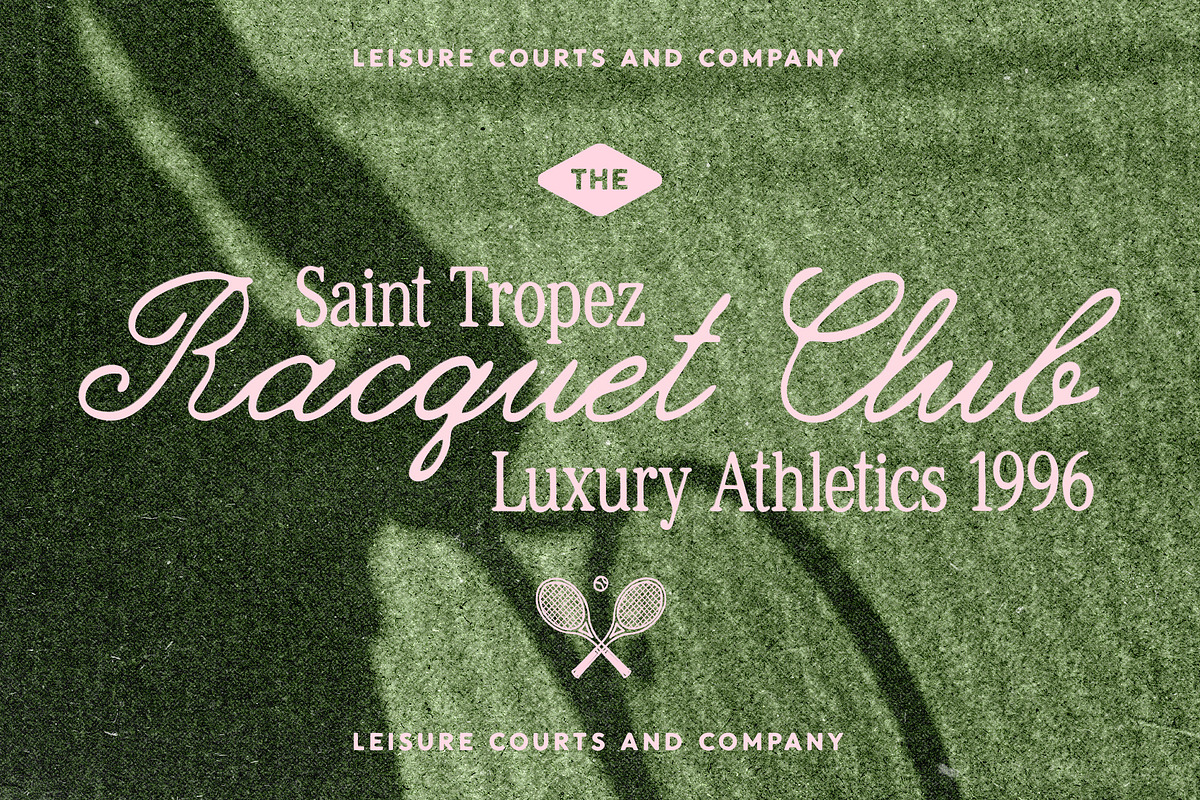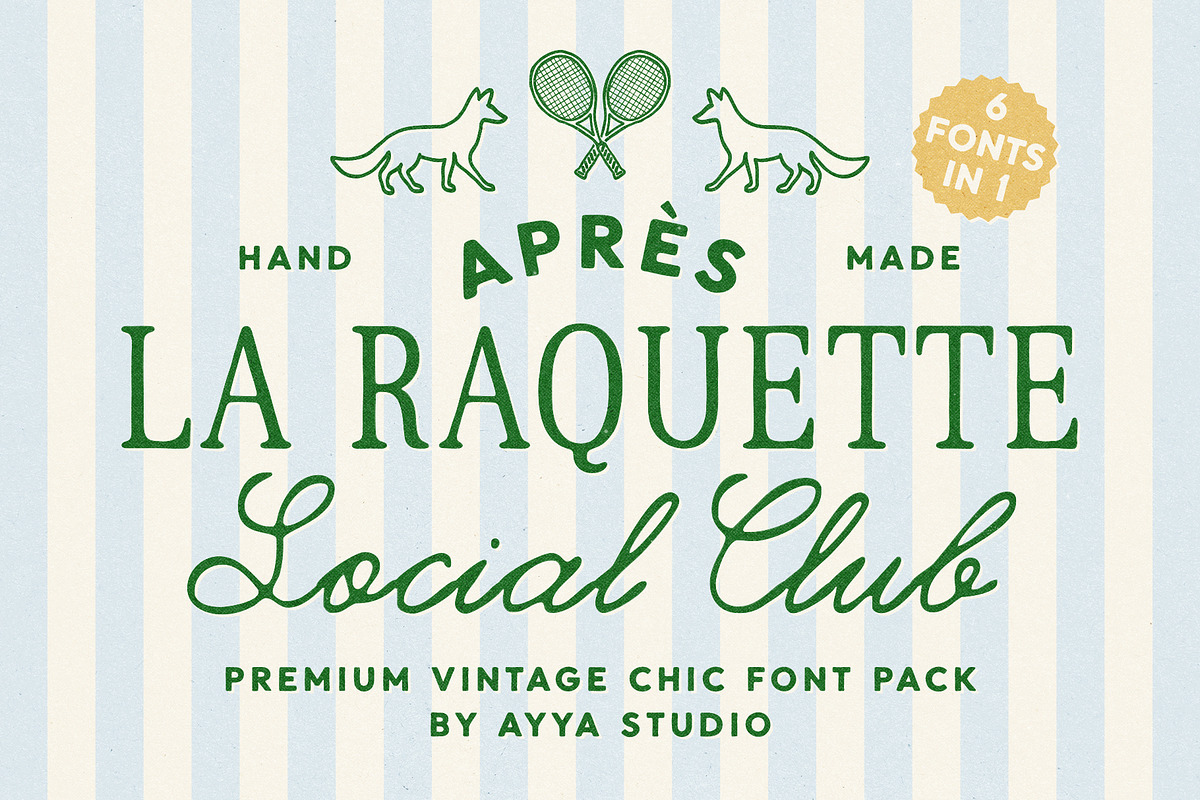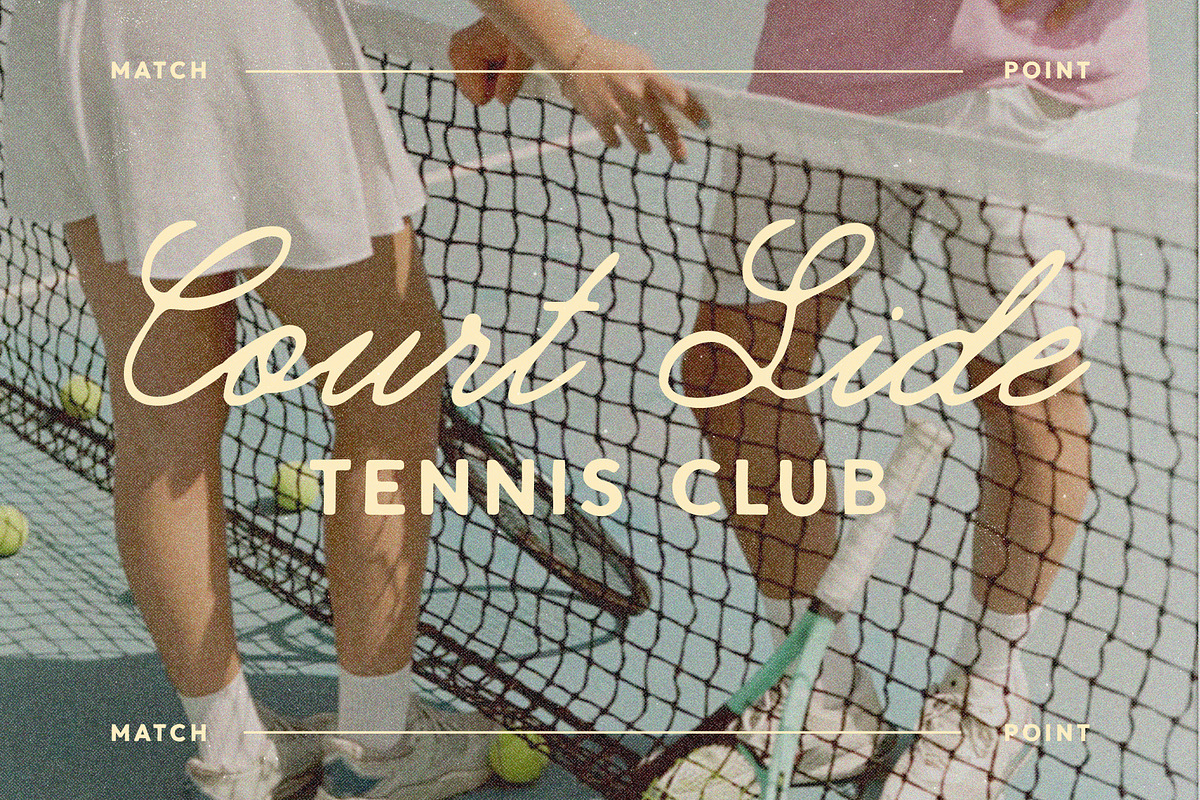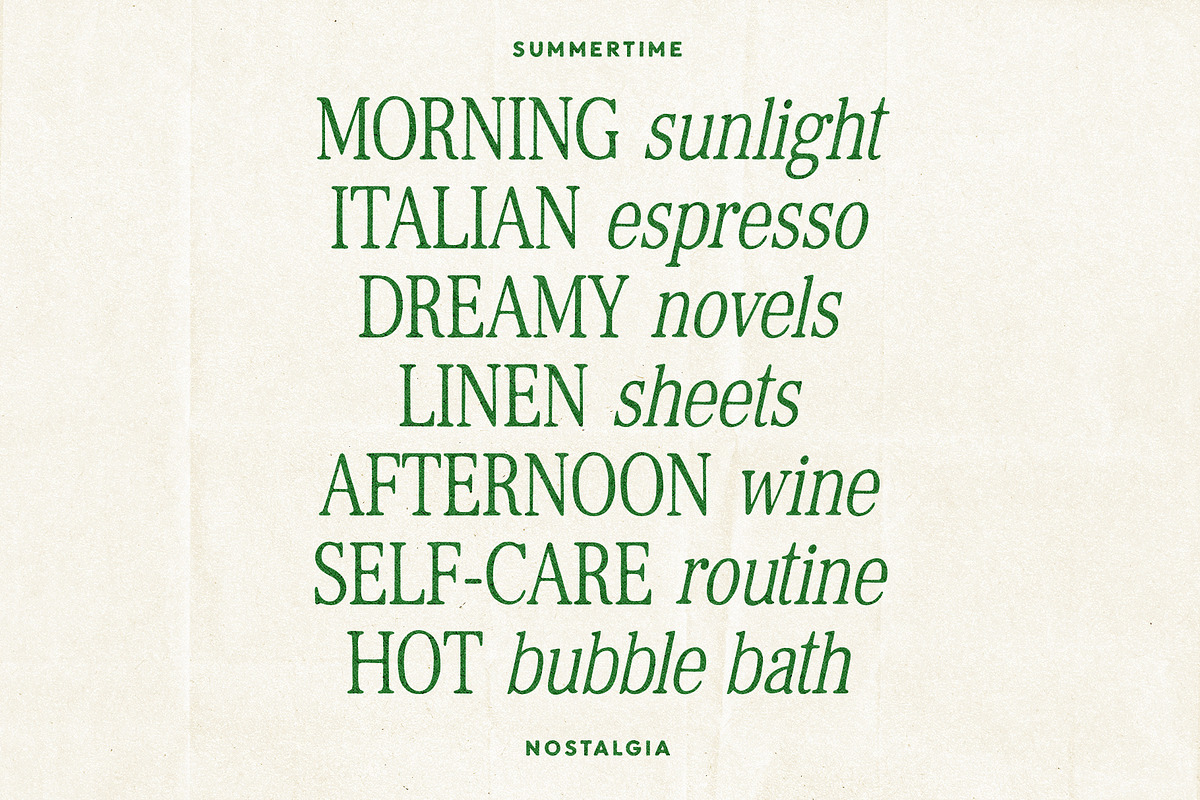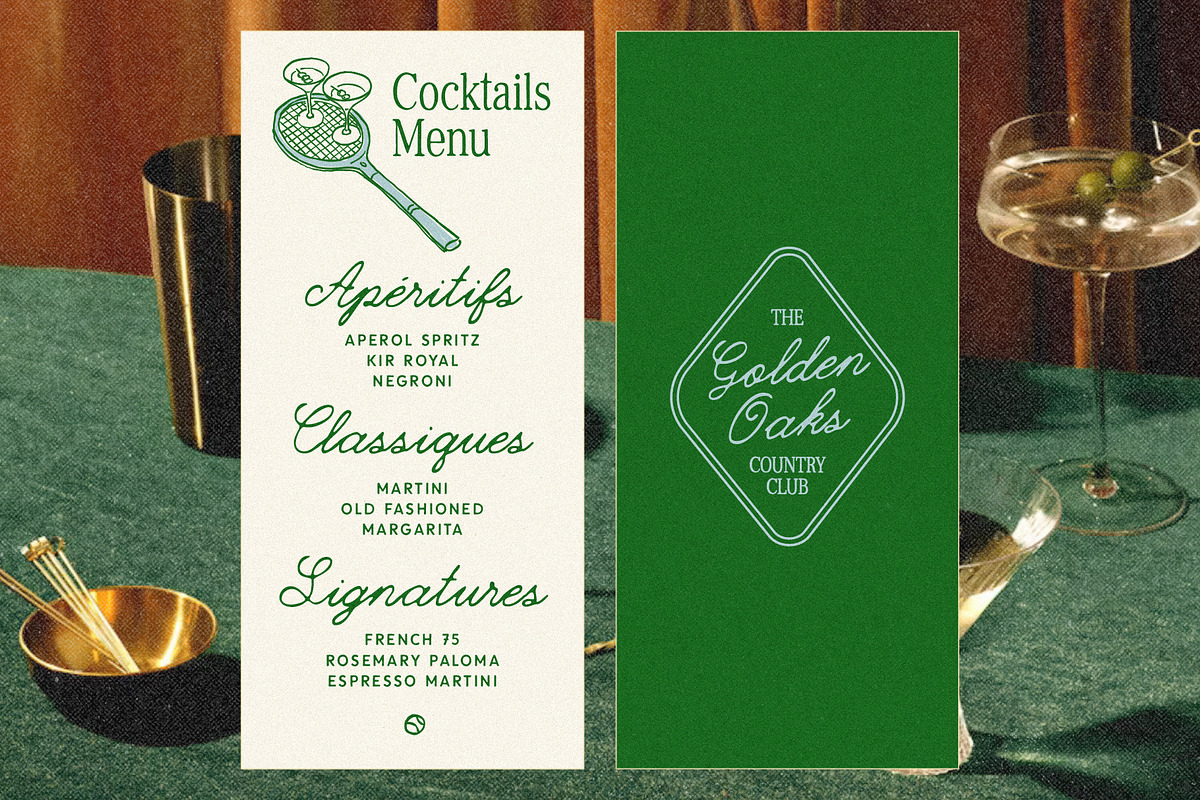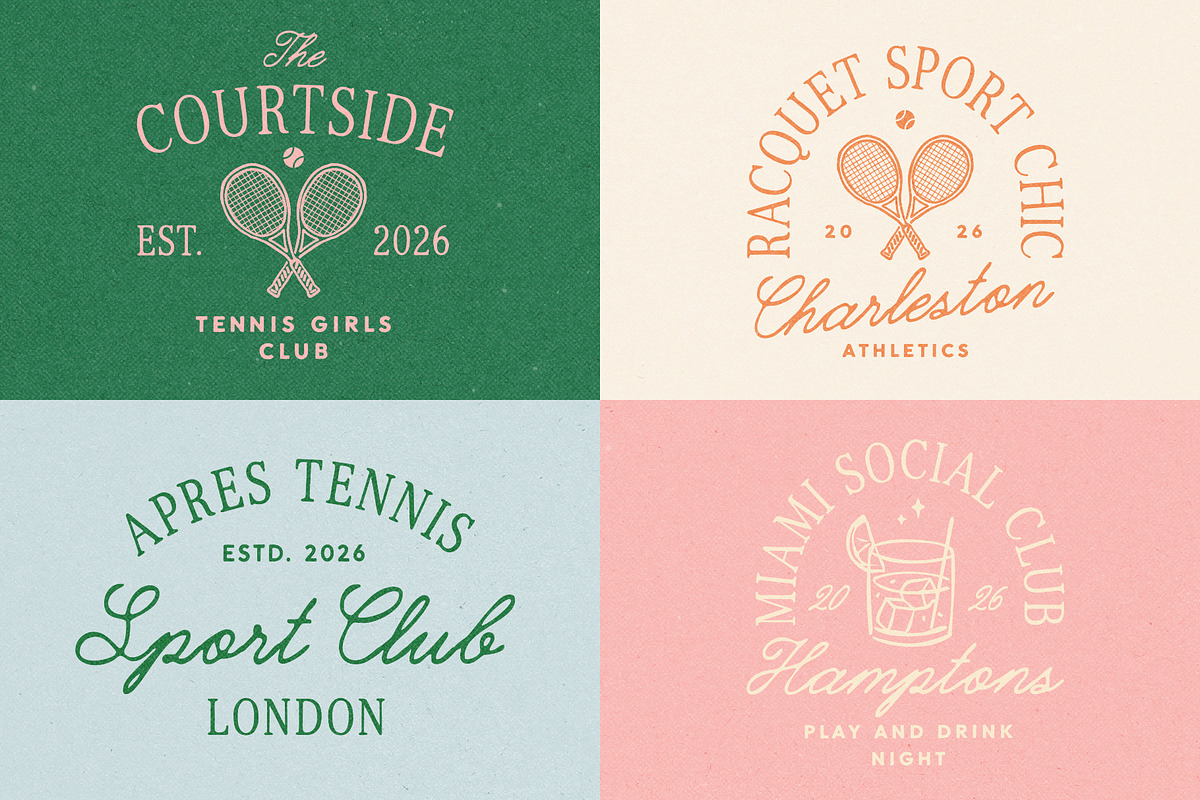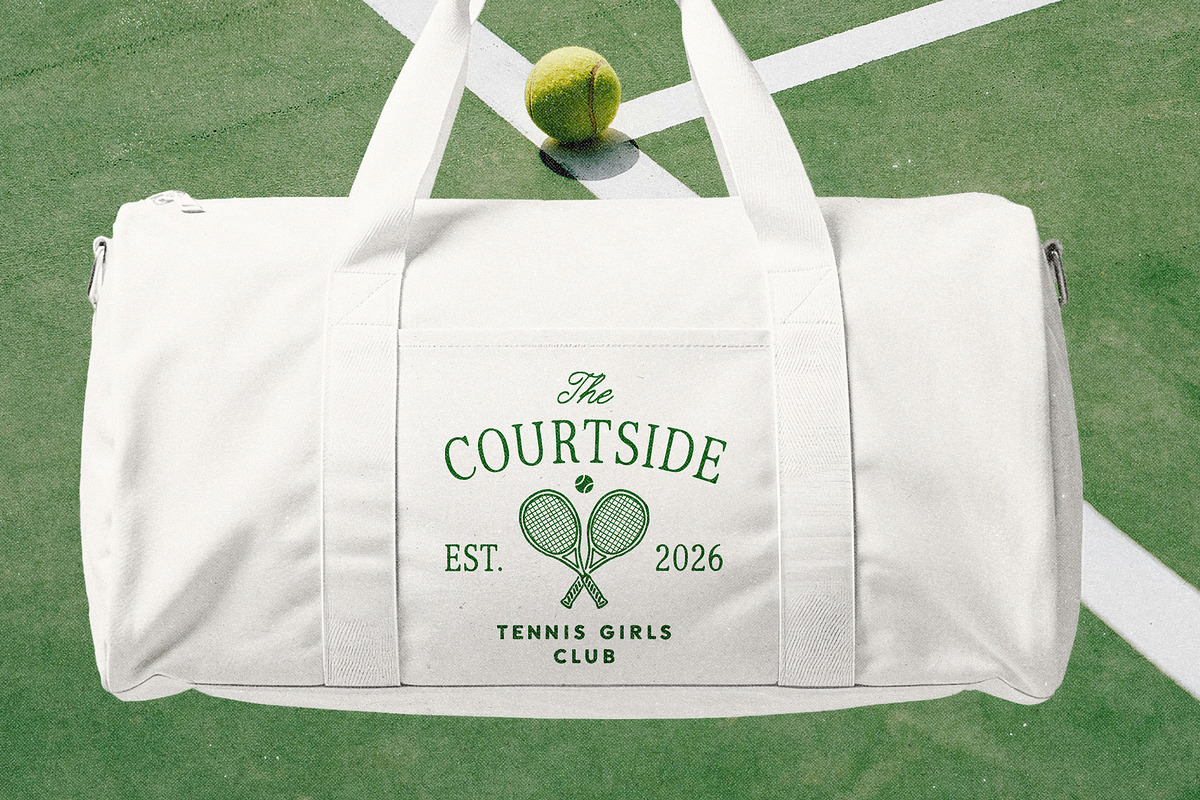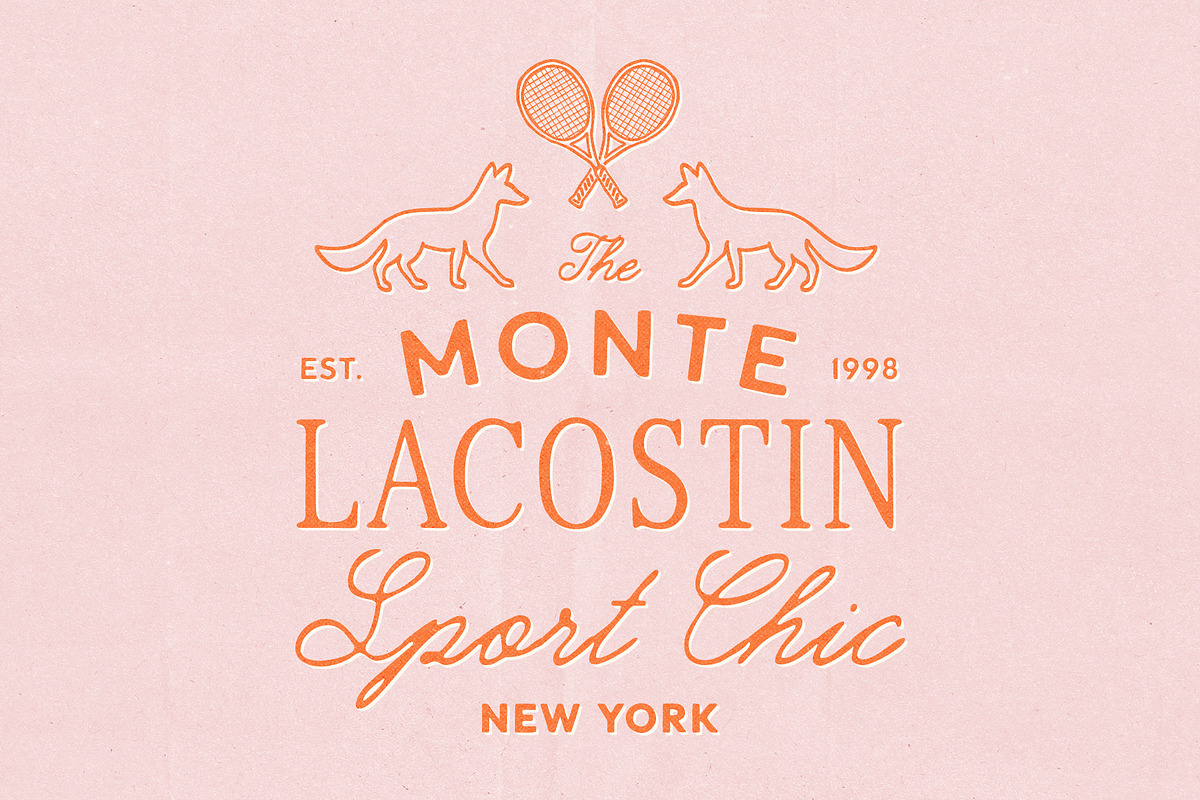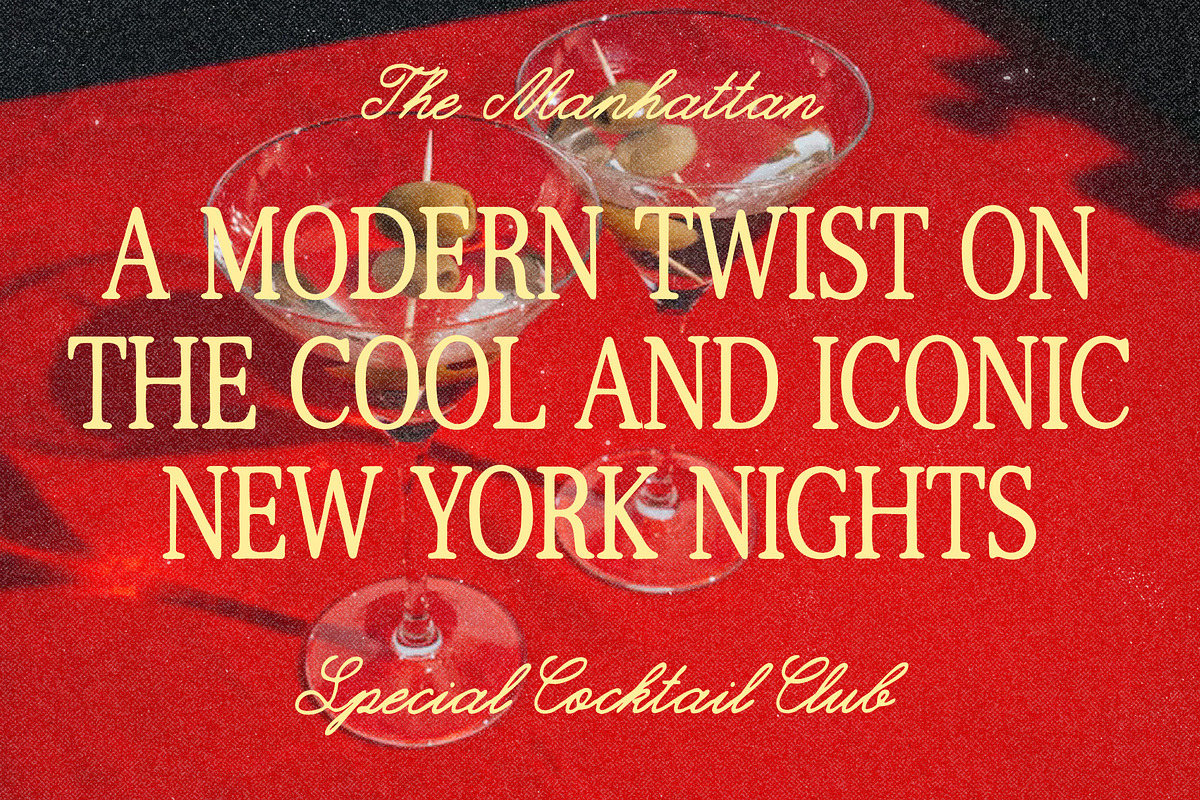
Handwritten Vintage Chic Font Bundle
Après La Raquette Social Club — это не просто еще один набор рукописных шрифтов, это целое семейство из 6 шрифтов, которые живут вместе, как члены частного клуба. Каждый шрифт имеет свой собственный голос, но вместе они создают систему, которую вы можете смешивать, сочетать и накладывать друг на друга для бесконечных вариаций.
Вдохновение черпается из загородных теннисных клубов с их сдержанной элегантностью, полосатыми пиджаками и выцветшими от солнца плакатами на стенах клубного дома. Этот баланс формальности и непринужденности сформировал эти шрифты: классические по своим корням, но нарисованные от руки, что придает им несовершенства, благодаря которым они кажутся живыми.
Эта серия названий полна контрастов — изысканная, но игривая, традиционная, но современная, ностальгическая, но удобная в современном контексте. Она несёт в себе винтажный дух с явным французским шиком, тяготея к эстетике «старых денег», но не будучи чопорной или предсказуемой.
Идеально подходит для проектов, где стиль имеет значение: брендинг с характером, логотипы, требующие изысканности с изюминкой, смелые редакционные плакаты, заметки в журналах, надписи на футболках или что-либо, заслуживающее нотки очарования и остроумия. Après La Raquette Social Club — это тот тип, который легко адаптируется — от элегантных меню до игривых заголовков — и всегда чувствует себя как дома.